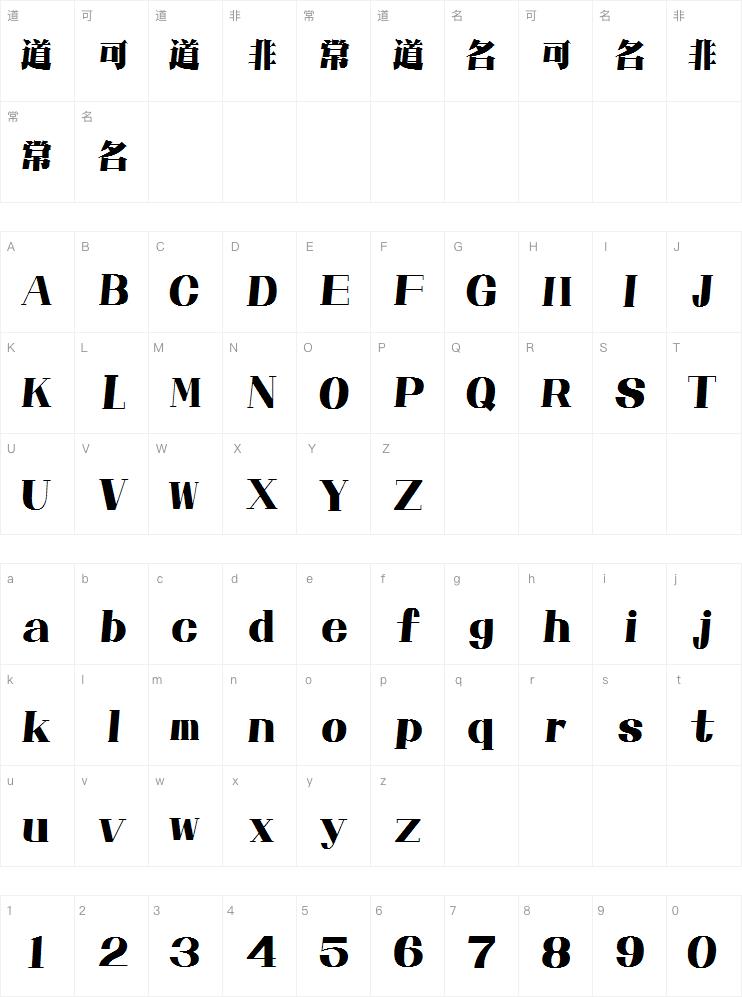
锐字摇滚滚石宋是一款风格前卫的创意斜宋体。字形左侧动态倾斜,中宫饱满,重心高扬,营造出动态、前进的视觉感,仿佛传递着向上的力量以及不断追求个性自由的摇滚精神;笔画造型菱角分明,直率有力,钩笔画造型简约,转折处方圆搭配,展现出简洁纯粹且自由不羁的个性风格。适用于音乐节宣传、海报设计、广告设计、网页标题、品牌标识等应用场景。